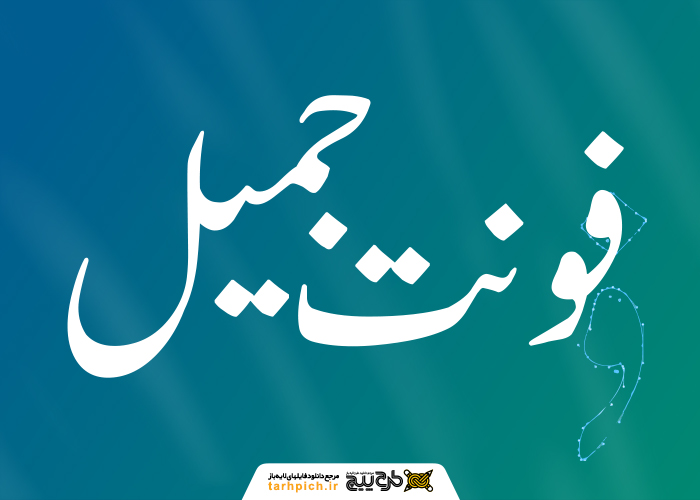
فونت جمیل
دانلود فونت فارسی جمیل با کیفیت بالا از سایت طرح پیچ امکان پذیر شد. بعد از دانلود فونت جمیل می‌توان لینک دانلود فونت کوفی را نیز دریافت کنید.فونت جمیل یکی دیگر از  فونت های  خانواده نستعلیق است .طراح این فونت آقای بشارت علی هستند.فونت جمیل در دسته بندی فونت های فارسی قرار دارد.اگر به دنبال دانلود فونت رایگان برای خود هستید کافیست روی لینک مربوطه کلیک نمایید.